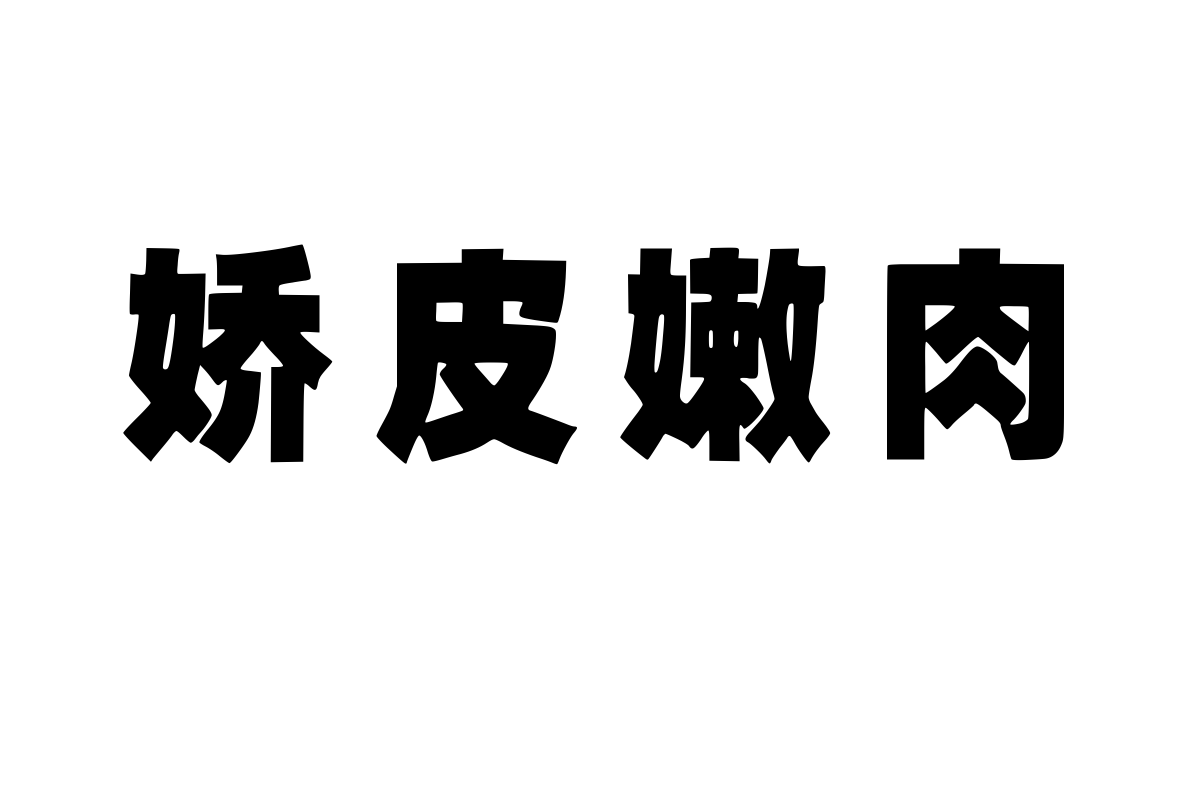
王天喜标题黑是一款具有深厚文化底蕴和艺术价值的中文字体,它以其独特的书法风格和精湛的技艺深受广大用户的喜爱。这款字体采用了传统的书法笔触和结构,将汉字的笔画、结构、章法等元素巧妙地融合在一起,形成了一种独特的美感。
在设计上,王天喜标题黑注重细节的处理和线条的流畅性,使得每一个字都显得生动而有力。它的字体结构严谨,笔画清晰,无论是在印刷还是电子屏幕上都能呈现出良好的视觉效果。同时,这款字体还具有很高的辨识度,能够很好地与其他字体区分开来。
此外,王天喜标题黑还具有很好的兼容性和适应性,适用于各种应用场景。无论是用于书籍、杂志、广告还是网页设计,都能够展现出其独特的魅力。同时,这款字体也适合用于商业用途,如商标、标志等,能够为品牌增添一份独特的个性和价值。
总之,王天喜标题黑是一款具有深厚文化底蕴和艺术价值的中文字体,它以其独特的书法风格和精湛的技艺赢得了广大用户的喜爱。无论是用于个人项目还是商业用途,它都能够为你的作品增添一份独特的魅力和价值。